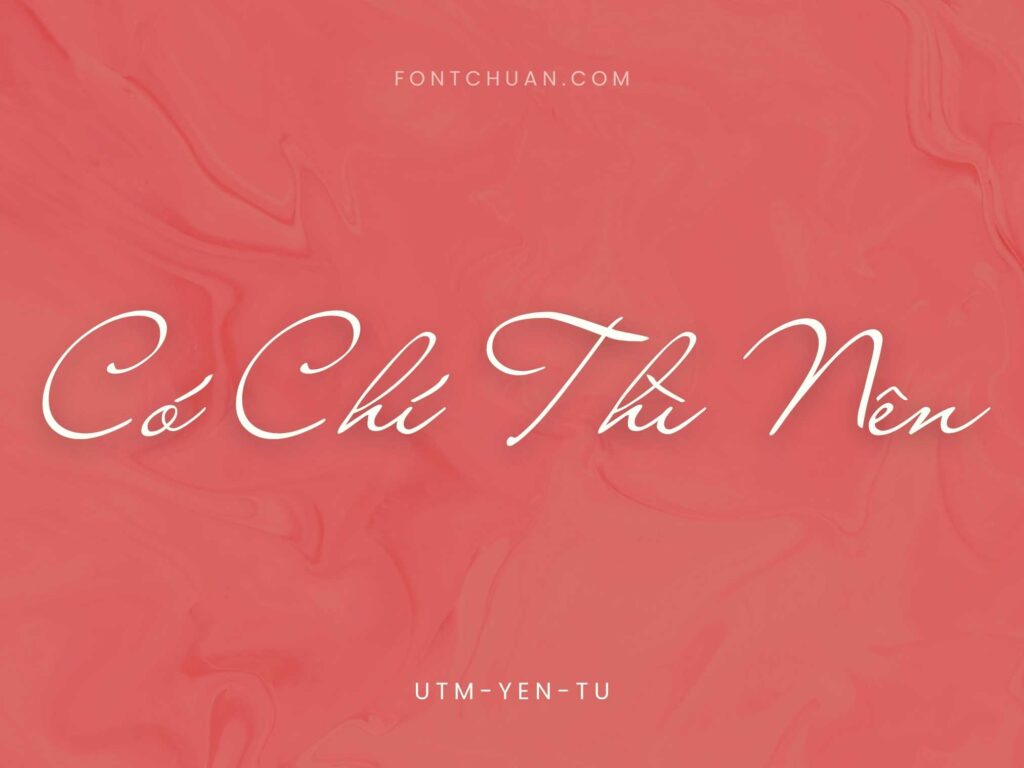
Font UTM Yen Tu Việt Hóa
Yen Tu là một font chữ viết tay độc đáo, được thiết kế bởi Michael Đinh Kiên. Font này mang phong cách thư pháp truyền thống, với các nét chữ mềm mại và uyển chuyển, tạo nên sự thanh thoát và tinh tế trong từng ký tự. Yen Tu phù hợp cho các dự án thiết kế mang đậm bản sắc văn hóa Việt Nam, như thiệp mời, thư pháp, hay các ấn phẩm nghệ thuật.
Font này đã được Việt hóa bởi Thiên Minh, đảm bảo hỗ trợ đầy đủ các dấu và ký tự tiếng Việt, mang lại trải nghiệm sử dụng hoàn chỉnh cho người dùng. Ngoài tiếng Việt, Yen Tu còn hỗ trợ nhiều ngôn ngữ khác, mở rộng khả năng ứng dụng trong các thiết kế quốc tế. Thành viên của Font Chuẩn đã sưu tầm và giới thiệu font này đến cộng đồng thiết kế, giúp họ có thêm lựa chọn cho các dự án sáng tạo. Với đường nét mềm mại và phong cách thư pháp đặc trưng, Yen Tu phù hợp cho các thiết kế thiệp mời, tiêu đề, poster, và các dự án cần sự tinh tế và nghệ thuật.